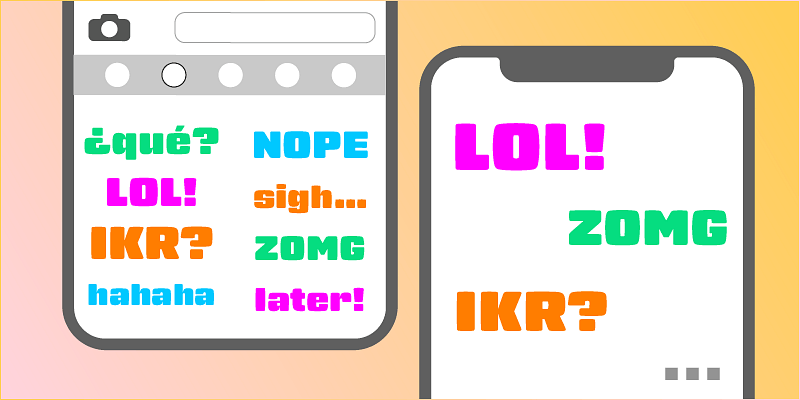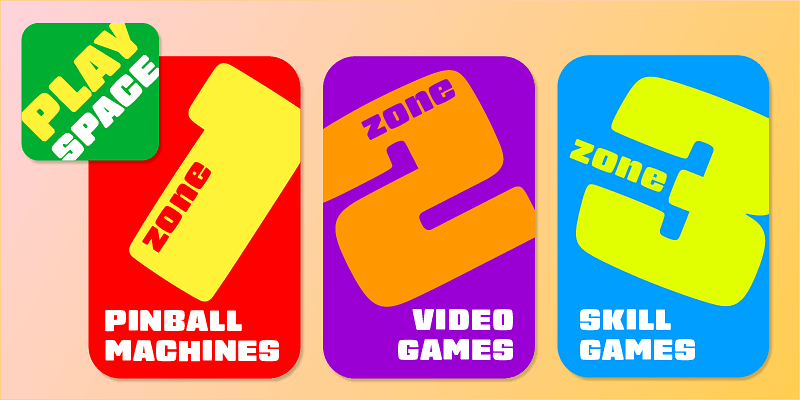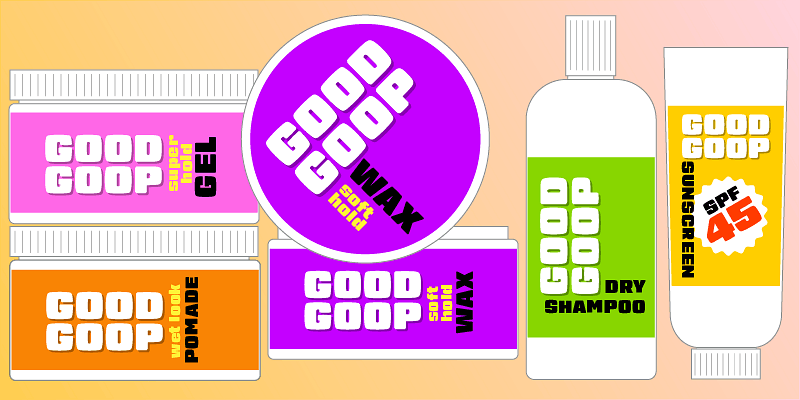
디스플레이 서체는 일반적으로 하나의 작업에 적합합니다. 디자이너가 가장 어둡거나 가장 얇은 활자 또는 가장 많은 스와시를 필요로 할 때 일반적인 활자가 적합할 수 있습니다. 그러나 James Puckett은 지속적인 가치를 지닌 새로운 한 가지 두께의 다재다능한 서체를 디자인하고 싶었습니다. 그는 서체가 모더니즘 가구처럼 참신하고 고전적으로 보이길 원했습니다. Gigalypse는 직선이 없는 정사각형인 squircle로 알려진 일종의 초타원에서 착상되었습니다. Gigalypse는 똑똑하고 진지하며 미래 지향적으로 보일 수 있습니다. 둥근 모서리와 곡선형 측면은 정교한 기하학으로 완화된 따뜻함과 유머를 더합니다. 이 부드러운 정교함은 두꺼운 디스플레이 서체가 필요할 때 Gigalypse가 적합하도록 합니다.